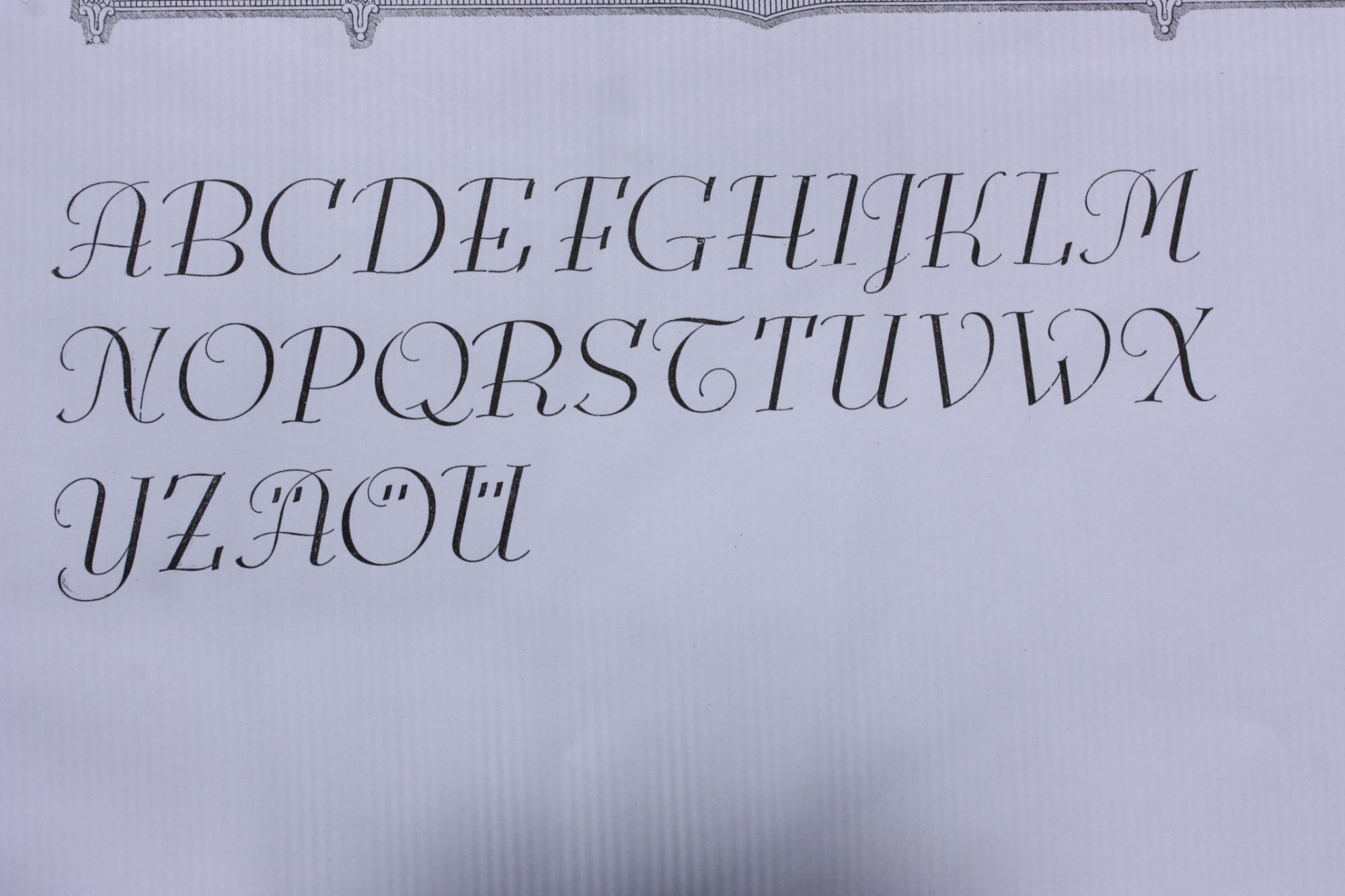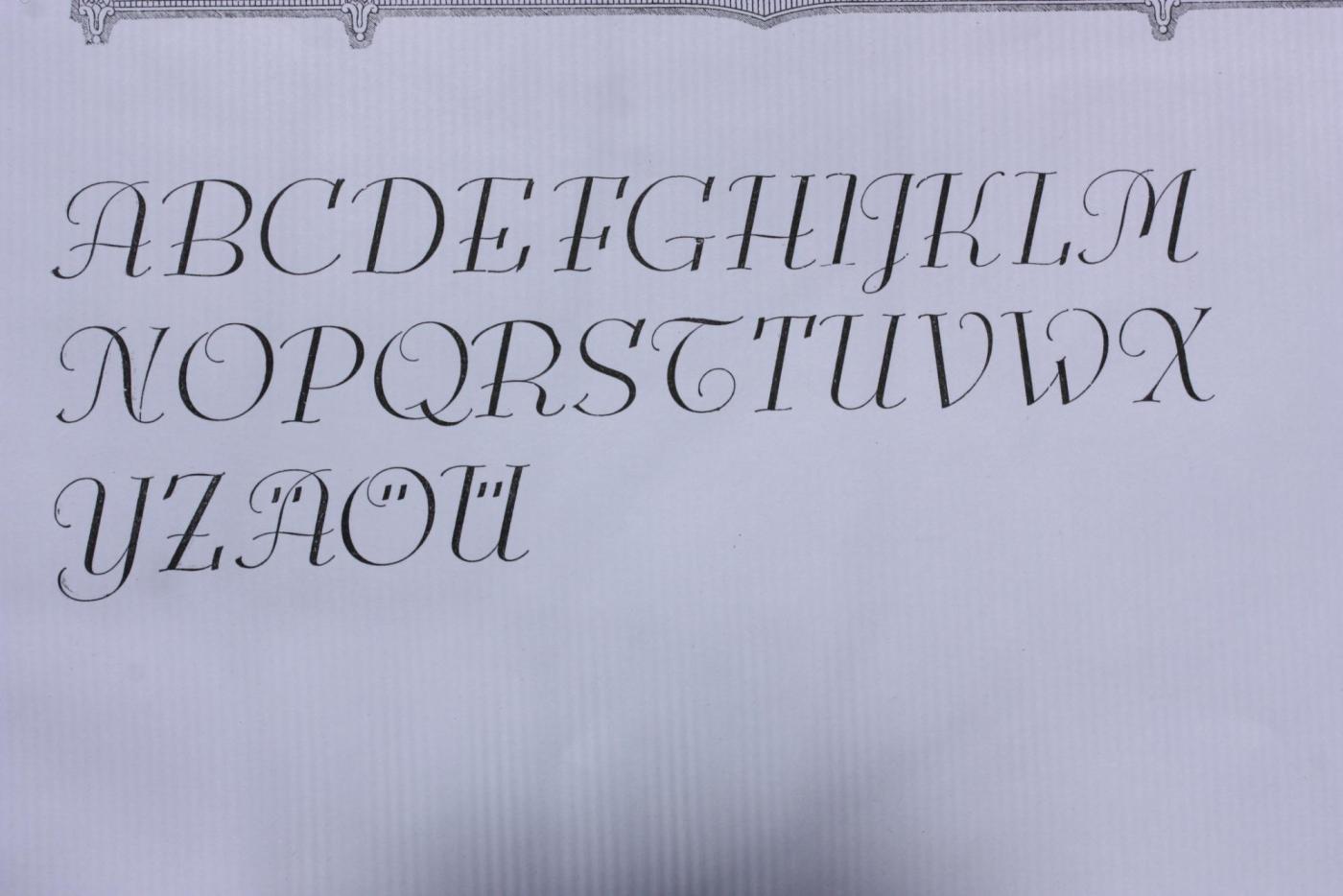
Buchdruckschrift in 48pt
die abgebildete Schrift ist ein "Scheunenfund" aus der Nordschweiz in 48 pt.  Leider gibt es keine Zahlen. Vermutlich stammt sie aus einer ehemaligen Druckerei in Winterthur. Ich konnte sie bisher nirgends identifizieren, der Entwurf könnte aus den zwanziger Jahren sein. Vielleicht hat jemand eine Idee ?IMG_2404.thumb.JPG.72de9adc04a5aeea2995c932a2067fff.JPG
Another jewel of the vast treasure of historical font designs was digged out and brought to life again. Due to the courtesy of the Quay Brothers, London, who yielded to me an age-old brochure of Albert Auspurg’s ‚Miami‘, released by Schriftguss in 1934, I was able to redesign this elegant font. This font which I called ‚Elbflorenz‘, a cognomen for Dresden, contains West and Central European type faces as well as those for Romanian and Turkish.